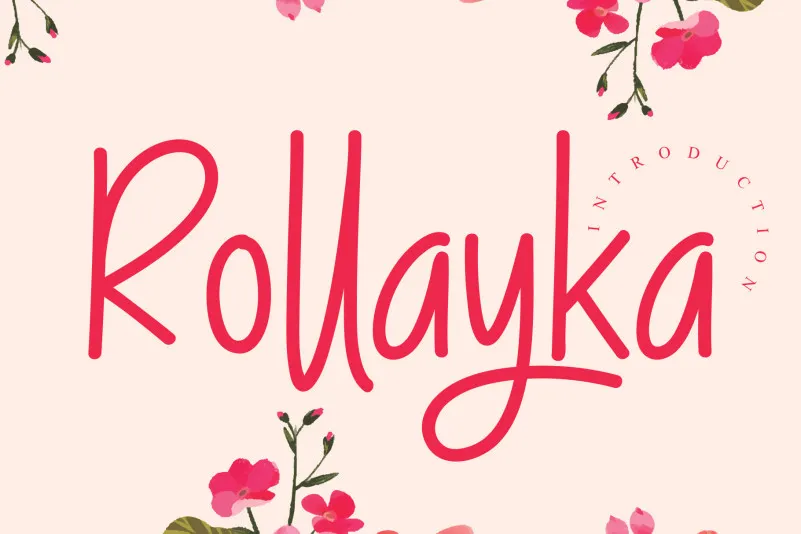
Rollayka Script Font – Download Grátis
A Rollayka Script Font é uma elegante fonte escrita a mão, altiva e receptiva. Esta escolha única é perfeita para quem busca um estilo versátil e criativo na sua próxima criação de design gráfico. Seus traços fluidos e amigáveis deixam seu trabalho com uma personalidade atraente e despojada. Com o Rollayka Script Font, você pode criar designs inovadores e surpreendentes que capturam os detalhes do seu projeto. Não perca tempo, crie algo único hoje mesmo com essa poderosa fonte.